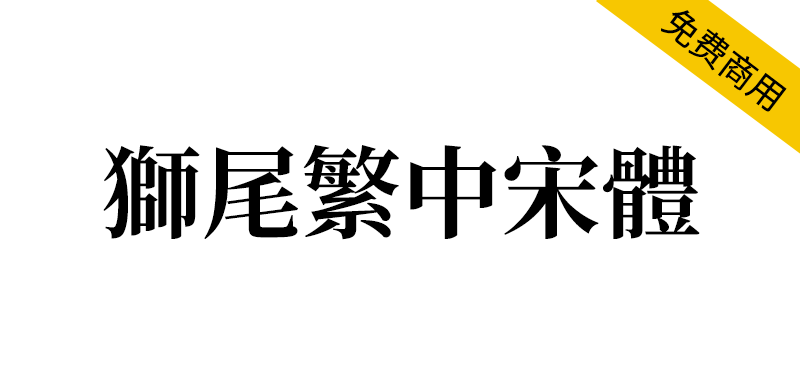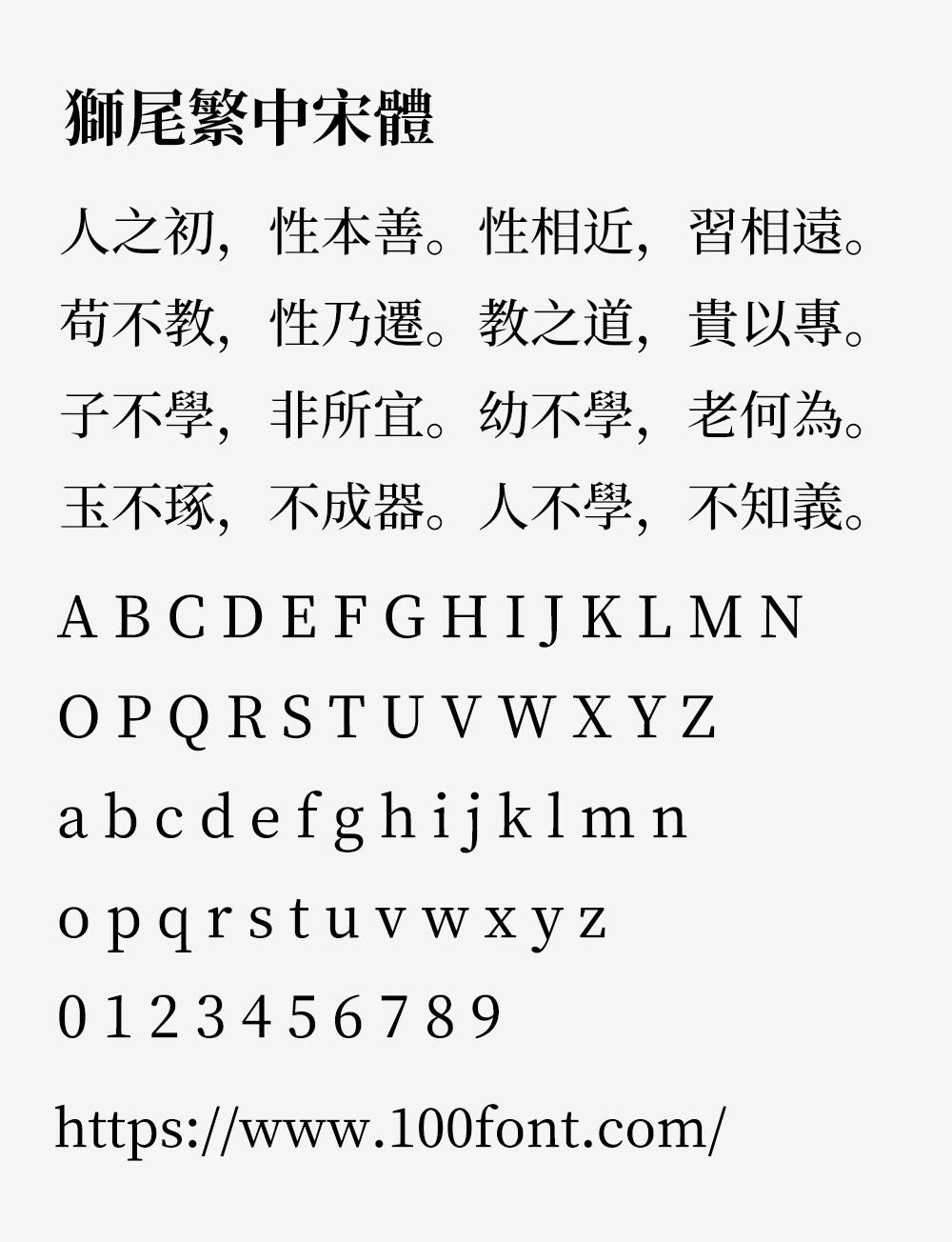
狮尾繁中宋体基于思源宋体的简转繁字型(简转繁的意思就是输入简体字时,会自动显示成繁体字),狮尾繁中宋体设计上针对笔画粗细有7种字重,所以不论大标、小标、简单的段落排版都能清晰辨识。可以免费商用,欢迎大家自由应用、自由优化、自由改作!
狮尾繁中宋体的特色是「简体字转成繁体字的字型档」,没有很完美,比完全没转换好一点,不能处理「一简对多繁」。可以处理「一简对多繁」的字型,请参考「繁媛明朝」专案。